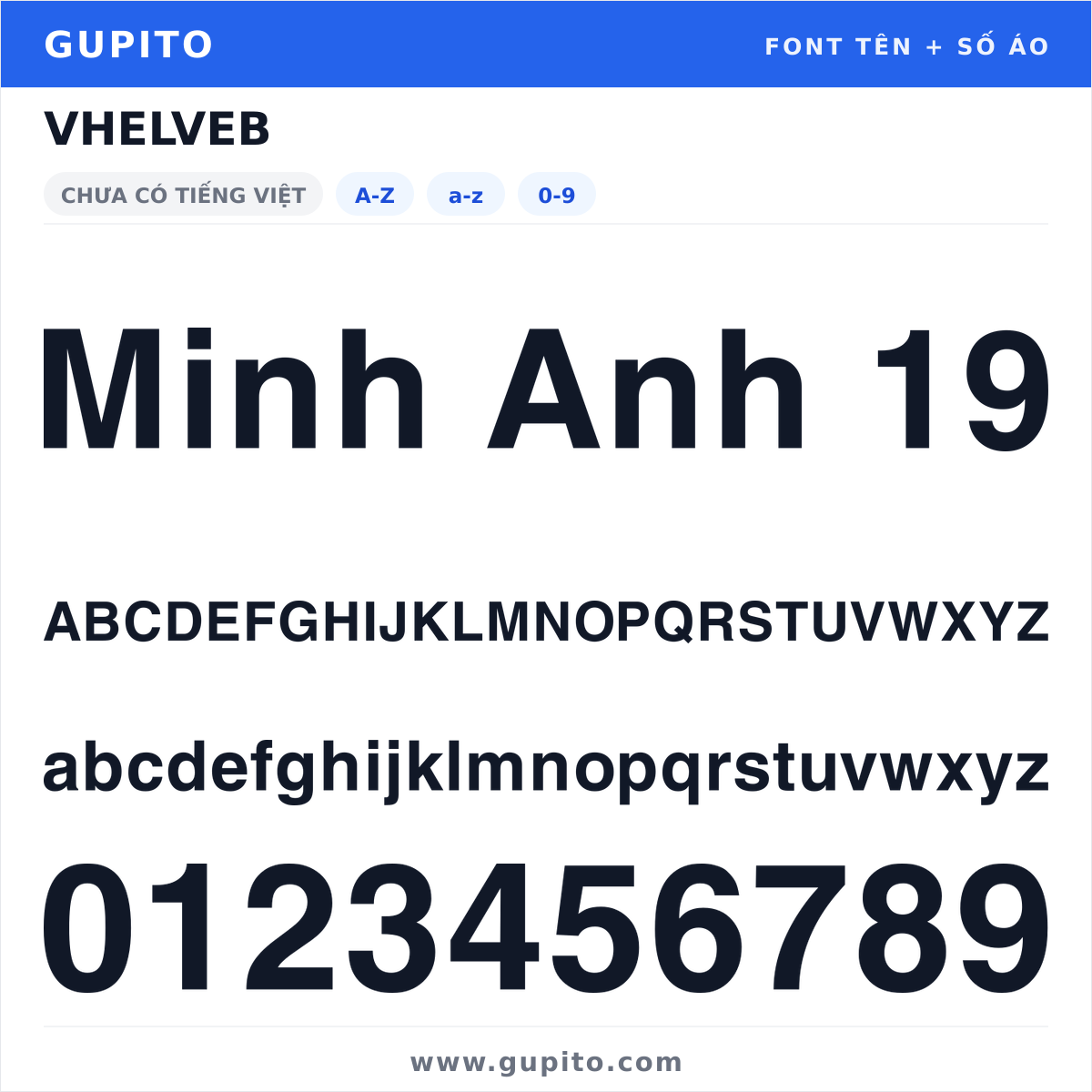
VNI-Helve-Bold
VNI-Helve-Bold · Font Vhelveb in tên áo bóng đá, áo lớp, số áo · chữ đậm thể thao
Font Vhelveb với nét chữ đậm, rõ ràng, có bảng số 0-9, lý tưởng để in tên và số áo bóng đá, áo lớp, quà tặng. Bộ chữ VNI-Helve-Bold dùng để in chuyển nhiệt lên áo đấu, áo lớp, áo nhóm và đồ thể thao theo yêu cầu. Kiểu dáng: chữ đậm thể thao. Font dùng cho chữ không dấu và số áo. Có đủ bộ chữ số để in số áo. Từ khoá liên quan: font vhelveb, font in tên áo, font in số áo, font áo bóng đá, font áo lớp, font chữ đậm, font thể thao, font có bảng số.